随着现代生活的飞速提高,设计越来越被重视,字体设计这一门学科也越来越走向光明,字体设计运用的范围非常的广泛,品牌、包装、海报等。
字体设计行业门槛低,会用一些设计软件PS、AI、CDR就可以设计字体。但是想要做的好需要大量的知识和练习,所以能坚持下来做出成绩的人并不多。所以想要学习字体设计必须知道一些基础知识,下面就为大家一一介绍。其中包括字体结构、重心、中心、中宫、字面、布白、字重等等。
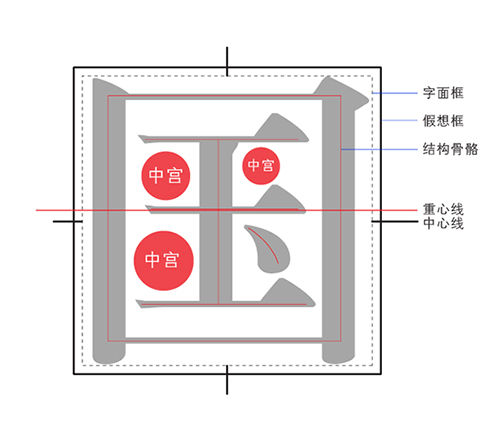
字体结构:也就是确定字的笔画组成的骨架、骨骼。根据汉字中笔画部件的多少,汉字可分为独体字和合体字。独体字只有一个部件,合体字有多个部件。
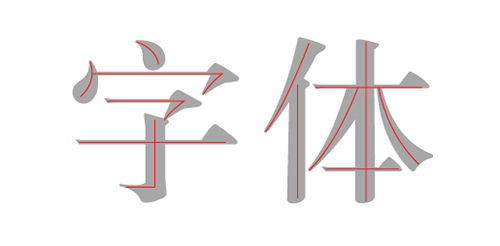
字体重心:就是整个字的分量的中心点。做字时把字的重心把握准了,做出的字才不会上歪下斜,左偏右倒,而显得平正。
字体中心:字体外框的水平与竖直中心线的交叉点,是一个绝对的点。重心相当于视觉中心,一般重心高于中心。
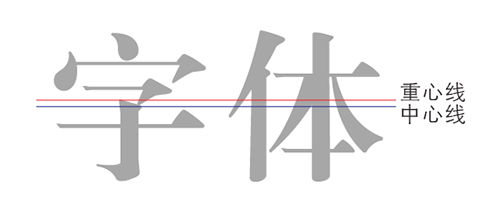
字体中宫:汉字笔画围成的空间。中宫的大小可以影响人们对字体本身的视觉感受。中宫大,笔画把字面框撑的较满,排版效果好,但容易呆板。而且字内留白大,字外围留白小,视觉上会挤压字间距,导致字间距过小,不利于阅读。中宫小,笔画排布舒展,字体看起来秀气,易于阅读。
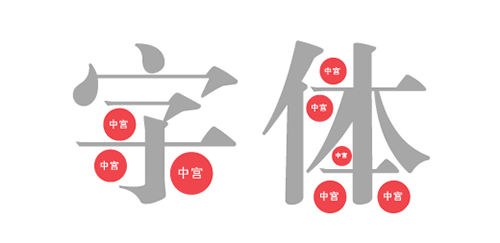
字面:字体轮廓的大小面积,决定字体的高矮胖瘦。
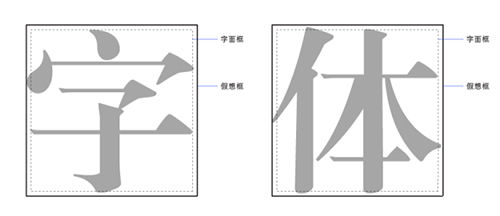
字重:汉字竖笔画的宽度和横笔画的高度的比例,可以影响字体的整体感受。
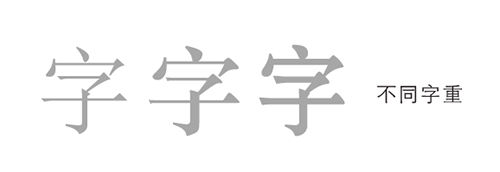
布白:字体设计中笔画与笔画之间的空白空间的分布安排。
图中有5条间隙相等的横线,当添加了4根竖线后就会发觉,贯通的间隙感觉白最大(1),半封闭的次之(2),中间截断的第三(3),全封闭的感觉最小(4),只要调整间隙使全封闭的为最大(1),中间截断的次之(2),半封闭的为第三(3),贯通的最小(4),白在视觉上就均匀了。如果把它当作一个字体来设计,就要考虑部件的个性、大小和参差关系,该宽的宽,该窄的窄。